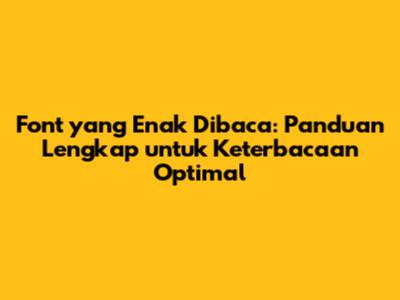
- Meningkatkan Keterlibatan Pengguna: Ketika teks mudah dibaca, pengguna akan lebih tertarik untuk membaca konten yang kamu sajikan. Mereka tidak akan merasa lelah atau frustasi, sehingga lebih lama berinteraksi dengan situs atau aplikasi kamu. Ini sangat penting, guys, karena semakin lama pengguna berinteraksi, semakin besar kemungkinan mereka untuk mencapai tujuan yang kamu inginkan (misalnya, membeli produk, mengisi formulir, atau sekadar menjelajahi situsmu).
- Meningkatkan Pemahaman: Font yang mudah dibaca membantu pembaca untuk memahami informasi dengan lebih cepat dan efisien. Mata tidak perlu bekerja keras untuk mengenali huruf dan kata, sehingga otak bisa fokus pada makna dari teks tersebut. Ini sangat krusial, terutama jika kamu menyajikan informasi yang kompleks atau teknis.
- Meningkatkan Citra Merek: Pemilihan font yang tepat mencerminkan profesionalisme dan perhatian terhadap detail. Ini bisa meningkatkan pengalaman pengguna dan membangun kepercayaan terhadap merekmu. Bayangkan, guys, jika situs web atau aplikasi kamu terlihat profesional dan mudah digunakan, orang akan lebih percaya pada produk atau layanan yang kamu tawarkan.
- Meningkatkan SEO (Search Engine Optimization): Meskipun tidak langsung, keterbacaan yang baik dapat berkontribusi pada SEO. Konten yang mudah dibaca cenderung mendapatkan lebih banyak waktu baca dan interaksi dari pengguna, yang pada gilirannya dapat meningkatkan peringkat situs webmu di hasil pencarian.
- Jenis Font: Ada dua kategori utama font: serif dan sans-serif. Font serif (misalnya, Times New Roman, Georgia) memiliki serif (garis kecil di ujung huruf), yang dapat membantu mata dalam mengikuti garis baca. Font sans-serif (misalnya, Arial, Helvetica) tidak memiliki serif dan cenderung terlihat lebih modern dan bersih. Pilihan antara keduanya tergantung pada konteks dan tujuan desainmu. Misalnya, untuk teks paragraf panjang, font serif mungkin lebih baik karena membantu keterbacaan. Sementara itu, font sans-serif bisa lebih cocok untuk judul, subjudul, atau tampilan di layar digital.
- Ukuran Font: Ukuran font sangat krusial. Pastikan ukuran font cukup besar agar mudah dibaca, terutama di perangkat seluler. Sebagai aturan umum, untuk teks tubuh, gunakan ukuran font minimal 16 piksel. Sesuaikan ukuran font dengan ukuran layar dan jarak pandang pengguna. Ingat, guys, tidak semua orang memiliki penglihatan yang sempurna, jadi berikan kemudahan bagi mereka untuk membaca kontenmu.
- Jarak Baris (Leading): Leading adalah jarak vertikal antara baris teks. Leading yang cukup memastikan bahwa baris teks tidak terlalu berdekatan sehingga sulit dibedakan. Leading yang ideal biasanya berkisar antara 1,2 hingga 1,5 kali ukuran font. Terlalu rapat akan membuat teks terlihat padat dan sulit dibaca, sementara terlalu lebar akan membuat teks terlihat terputus-putus.
- Jarak Huruf (Kerning dan Tracking): Kerning adalah penyesuaian jarak antara dua huruf tertentu, sedangkan tracking adalah penyesuaian jarak antara semua huruf dalam satu kata atau frasa. Pastikan jarak antar huruf cukup untuk membedakan huruf dengan jelas. Terkadang, beberapa font memiliki kerning yang buruk, sehingga perlu disesuaikan secara manual.
- Panjang Garis (Line Length): Panjang garis teks juga mempengaruhi keterbacaan. Garis yang terlalu panjang atau terlalu pendek dapat membuat mata lelah. Idealnya, panjang garis teks adalah sekitar 50-75 karakter per baris. Ini membantu mata untuk lebih mudah mengikuti garis baca dan meminimalkan kemungkinan mata melompat ke baris yang salah.
- Kontras Warna: Pastikan ada kontras yang cukup antara warna teks dan latar belakang. Kontras yang rendah akan membuat teks sulit dibaca. Gunakan kombinasi warna yang mudah dilihat, misalnya teks hitam pada latar belakang putih atau teks putih pada latar belakang gelap. Hindari kombinasi warna yang terlalu mencolok atau sulit dilihat, seperti merah pada hijau atau biru pada ungu.
- Georgia: Font serif yang sangat populer karena keterbacaan yang baik, bahkan pada ukuran kecil. Cocok untuk teks paragraf panjang.
- Times New Roman: Font serif klasik yang masih banyak digunakan karena kejelasan dan kemudahannya dibaca. Tapi, guys, mungkin sudah agak ketinggalan zaman, ya.
- Book Antiqua: Font serif yang elegan dan mudah dibaca, sering digunakan untuk buku dan dokumen formal.
- Arial: Font sans-serif yang sangat populer dan mudah dibaca. Tersedia di berbagai sistem operasi dan perangkat, sehingga sangat kompatibel.
- Helvetica: Font sans-serif yang klasik dan serbaguna. Terkenal karena kejelasan dan tampilannya yang modern.
- Open Sans: Font sans-serif yang dirancang khusus untuk keterbacaan di layar digital. Sangat populer di kalangan desainer web.
- Roboto: Font sans-serif yang modern dan mudah dibaca, banyak digunakan oleh Google.
- Lato: Font sans-serif yang ramah dan mudah dibaca, cocok untuk berbagai keperluan desain.
- Montserrat: Font sans-serif yang kuat dan modern, cocok untuk judul dan heading.
- Raleway: Font sans-serif yang elegan dan serbaguna, cocok untuk berbagai keperluan desain.